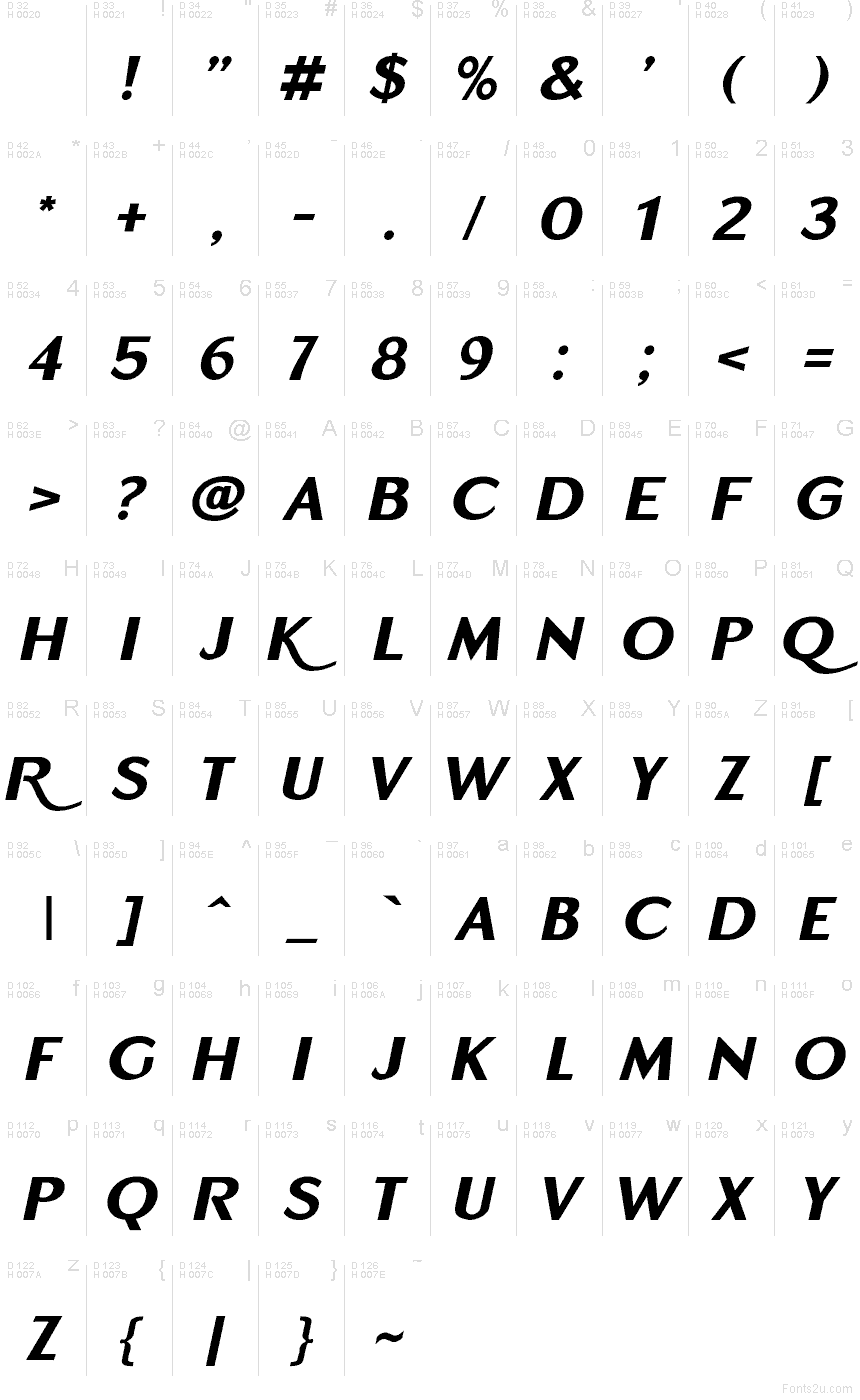
Emerald Crown Bold Italic, creata da Muhamad Fikry Nuralif di Fikryal Studio, è un carattere sans serif corsivo gratuito della famiglia Emerald Crown, caratterizzato da un'inclinazione scattante. Le lettere appaiono ampie e aerodinamiche, con bordi netti e un ritmo serrato che ricorda le linee di velocità: una scelta decisa, senza fronzoli.
Usa Emerald Crown Bold Italic per dare slancio ai tuoi titoli nel branding sportivo, poster di gare, team di e-sport, lanci tecnologici, etichette streetwear, packaging di energy drink e thumbnail di YouTube di grande impatto. Impostala con un po' di spaziatura in maiuscolo per lasciare che l'inclinazione respiri, e abbinala a un font grottesco regolare e sobrio per il testo principale, in modo che questo carattere gratuito resti il protagonista assoluto.